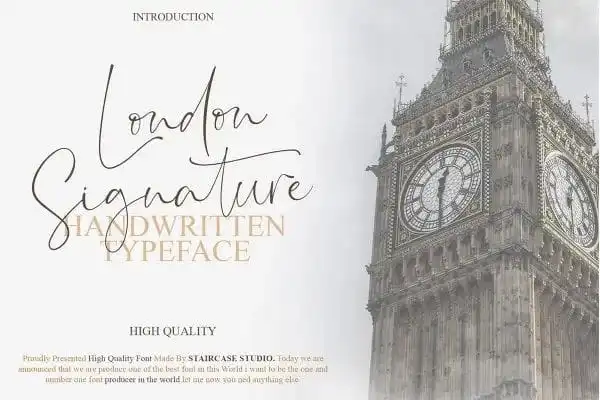
London Signature Font – Download Grátis
A Londres Signature Font é uma fonte que remete à arte do xilográfico, com sua textura ágil e elegante, inspirada nas características brilhantes de canetas plásticas ou esboços. Ela é perfeita para projetos que exigem um visual sofisticado e contemporâneo. Criada por Staircase Studio, uma font designer conhecida, esta coleção de letras e números é especialmente adequada para Logotipo, Design de Marca, Desenho de Logomarca, Arte de Letras Digitais, T-Shirts e Vestuário, Cartazes, Revistas, Sinais e Design Publicitário. A Londres Signature Font é uma escolha ideal para qualquer necessidade gráfica que exija um estilo moderno e atraente. Seja você designer ou criador de arte digital, esta fonte será uma opção perfeita para dar vida a seus projetos, oferecendo tanto qualidade quanto originalidade. Se estiver procurando por uma fonte que possa transmitir sua mensagem de maneira sofisticada e moderna, esta Londres Signature Font pode ser justamente o que você precisa.